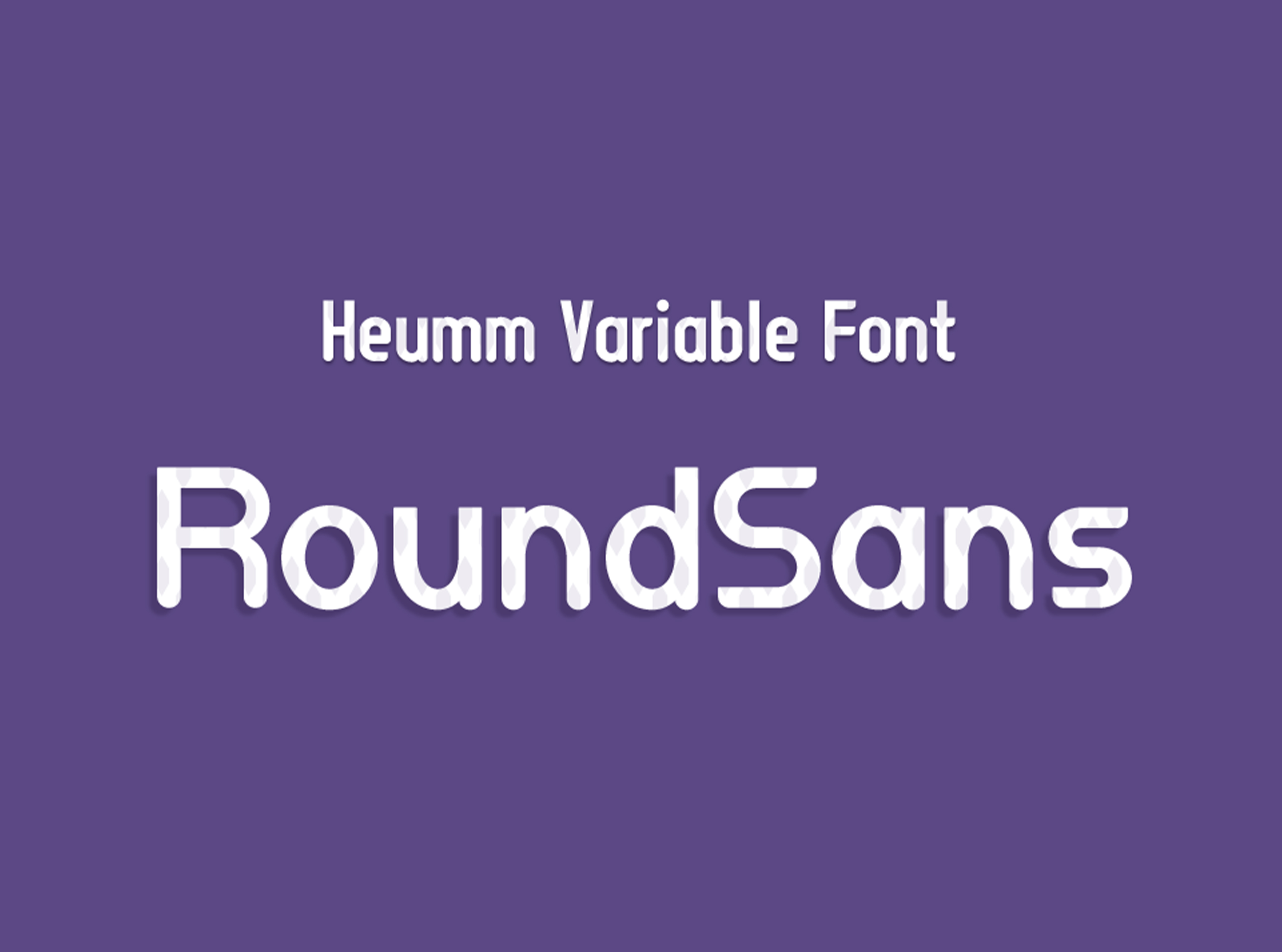
폰트 HURoundsans
굵기 140종
기간 2022
구성 영문 94자
특수문자 58자
영문확장 209자
가변글꼴 기술이 들어간 폰트로 영문과 영문확장만 제작이 되어있는 폰트로 영어 외에도 독일어, 프랑스어, 스페인어등에 호환됩니다.
variable(배리어블) 폰트는 가변형 폰트입니다.
사용자가 직접 굵기, 기울기, 너비를 임의로 조절이 가능하여 다양한 종수를 경험할 수 있습니다.
영문 전용 폰트로 라틴 알파벳만 제작되어
영어와 유럽권 내 독일어, 프랑스어, 스페인어, 루마니어 등을 위하여 사용할 수 있고 그 외의 라틴 알파벳도 사용 가능합니다.
HU Roundsans는 굵기, 너비, 기울기까지 조절이 가능하며
로고디자인, 웹디자인, 헤드라인, 본문 등 다양한 곳에서 활용이 가능합니다.